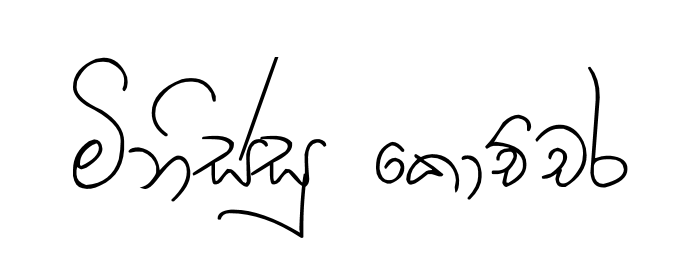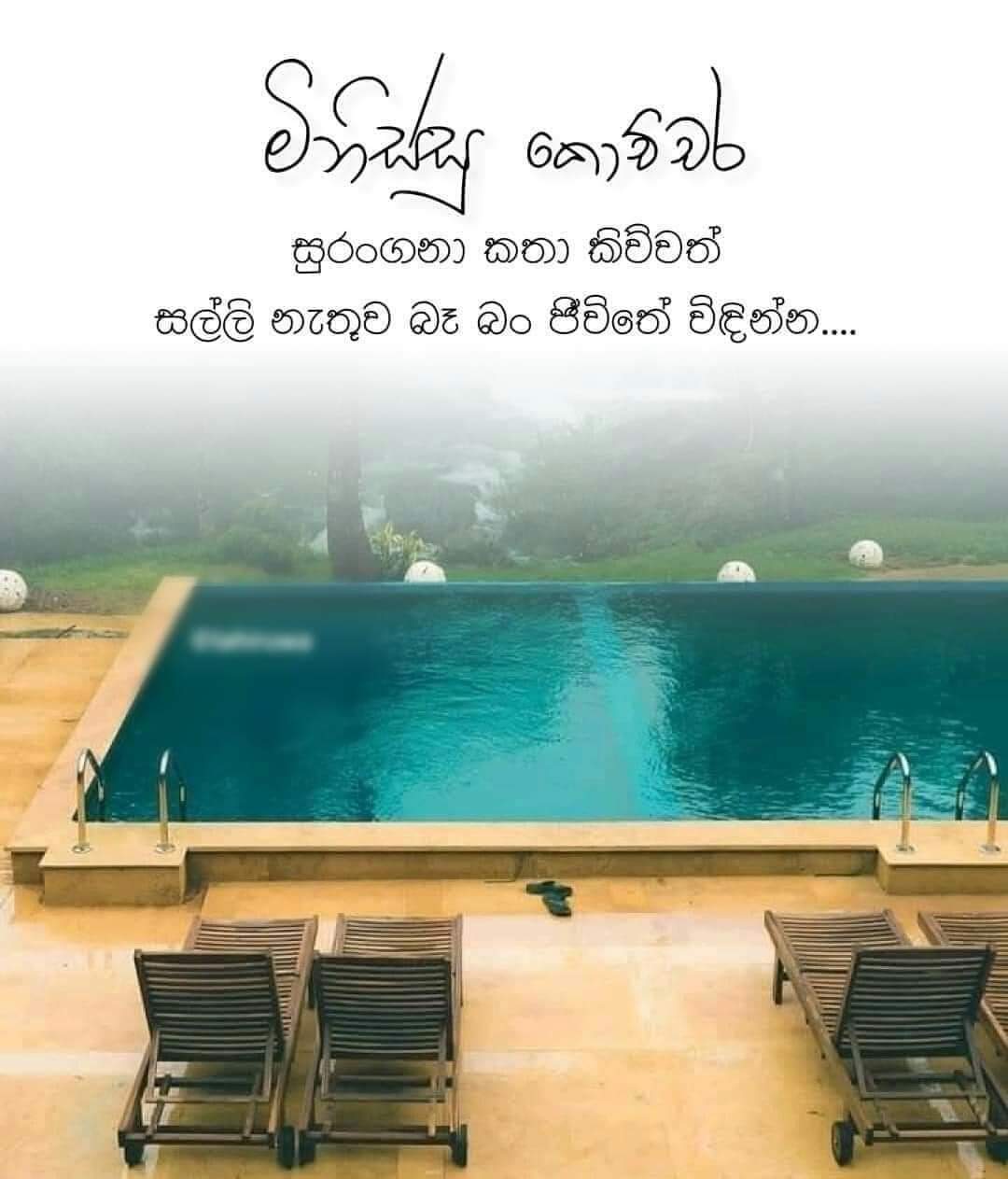
මේ සිංහල fonts 2 තියෙන පින්වතෙක් ලබා දෙන්නකෝ...
Anathai Well-known member Mar 28, 2021 5,519 7,891 113 Feb 28, 2022 #1 මේ සිංහල fonts 2 තියෙන පින්වතෙක් ලබා දෙන්නකෝ... Reactions: Ryan08
gayanwin Well-known member Jan 4, 2009 2,563 383 83 Kurunegala Feb 28, 2022 #2 me isiwara font eka neda ------ Post added on Feb 28, 2022 at 1:39 PM
sandaru1rox Well-known member Dec 11, 2011 7,401 2 3,267 113 Feb 28, 2022 #3 uda font eka nan athin liyalada manda bn "ච" akuru 2ka balapanko.
gayanwin Well-known member Jan 4, 2009 2,563 383 83 Kurunegala Feb 28, 2022 #4 meka harida https://font.akasa.lk/pawana.font ------ Post added on Feb 28, 2022 at 1:48 PM Reactions: sandaru1rox and Anathai
Anathai Well-known member Mar 28, 2021 5,519 7,891 113 Feb 28, 2022 #5 gayanwin said: View attachment 162127 meka harida https://font.akasa.lk/pawana.font ------ Post added on Feb 28, 2022 at 1:48 PM Click to expand... ade thanks .ban.dewei eka nadda?